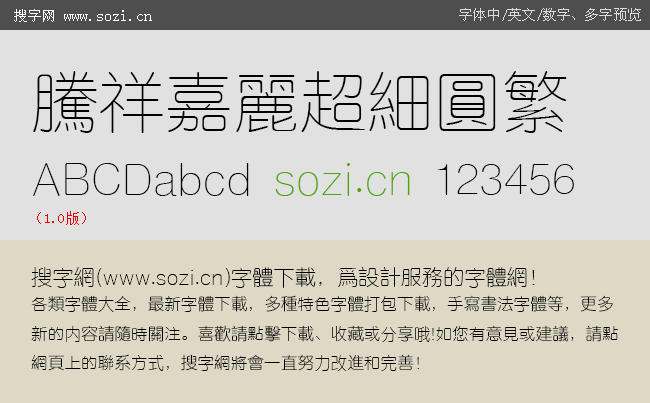
騰祥嘉麗超細圓繁
搜字網(wǎng)提供一款騰祥嘉麗超細圓繁字體下載,該字體每個漢字都經(jīng)過精心設計,筆畫粗細均勻、結(jié)構(gòu)美觀。每個字的圓角、圓頭、勾形都極光潔、風格統(tǒng)一,字形放大不變形,縮小顯示清晰,適用于樣本畫冊,報紙排版,網(wǎng)頁標題等廣告設計應用。